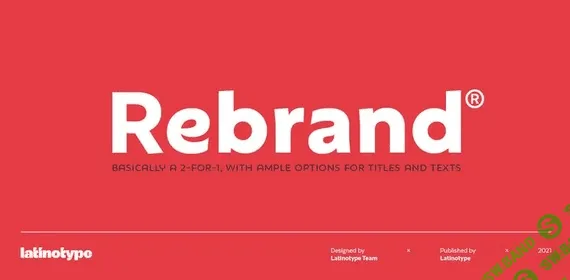
Название: Rebrand Font (2021)
Rebrand - это геометрия, типографика, которая придает уверенности. Однако, в отличие от чистой, холодной математики, этот шрифт стремится к более веселому и дружелюбному лицу.
Цель Rebrand - предложить геометрический шрифт Sans Serif, который может работать в различных ситуациях, от символов и заголовков до текста и всего, что между ними. Он также создает много индивидуальности, идеально подходящей для брендинга.
Существует две версии:
Display, которая является более плавной и динамичной, с девятью запрограммированными весами для широкого спектра интенсивности. Эта версия также имеет различные альтернативные символы и штрихи.
Текстовый, который имеет тот же настрой, что и Display, но немного более серьезный, с семью запрограммированными весами для обеспечения отличительных крайних тонов и тонких вариаций среди средних тонов.
Оба варианта охватывают основную кириллицу и имеют малый прописной шрифт. Оба создают одну феноменальную типографику: Rebrand.